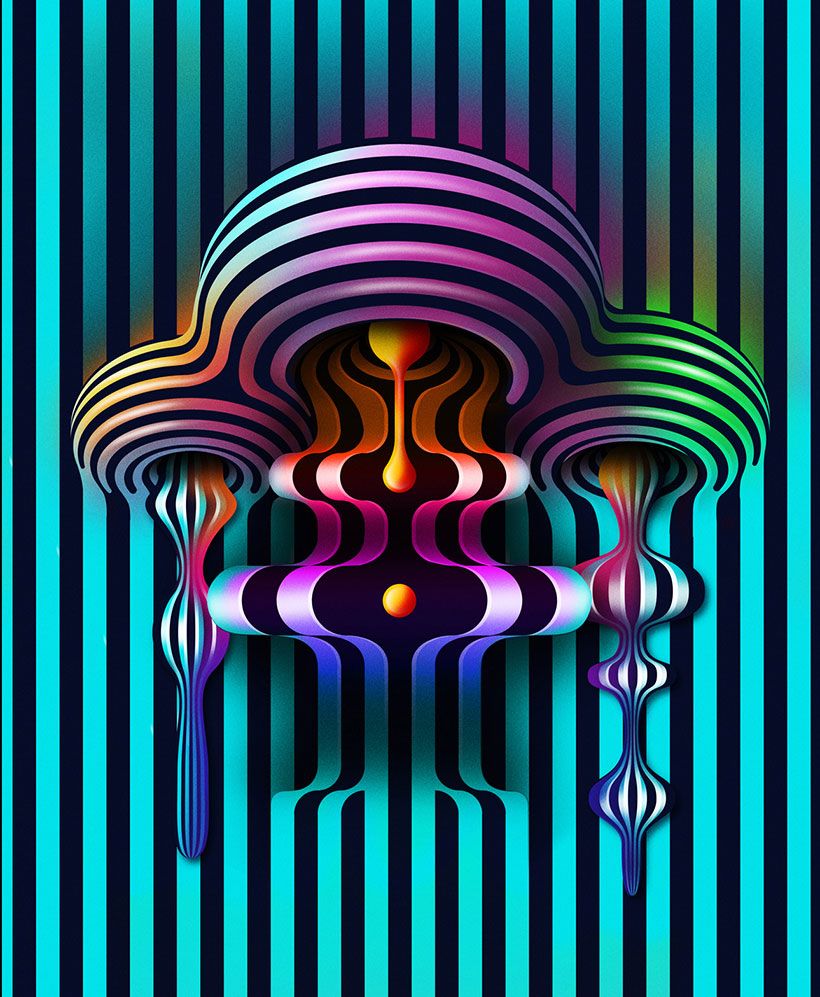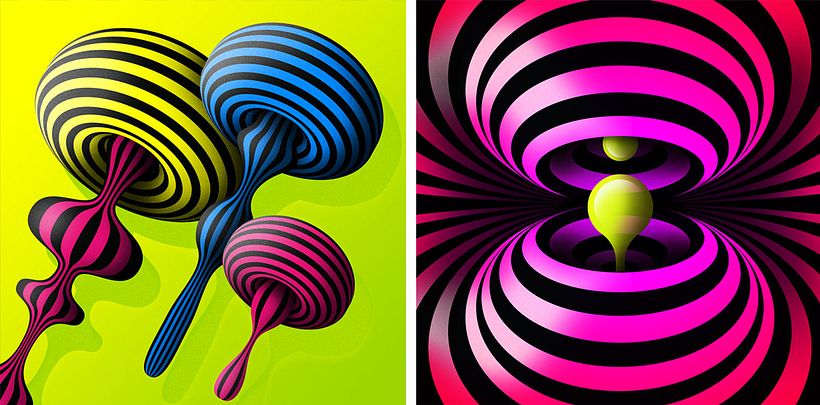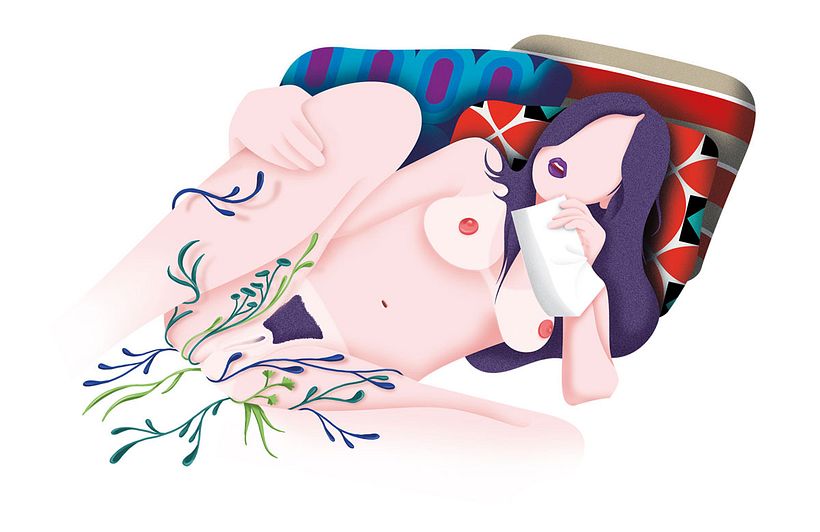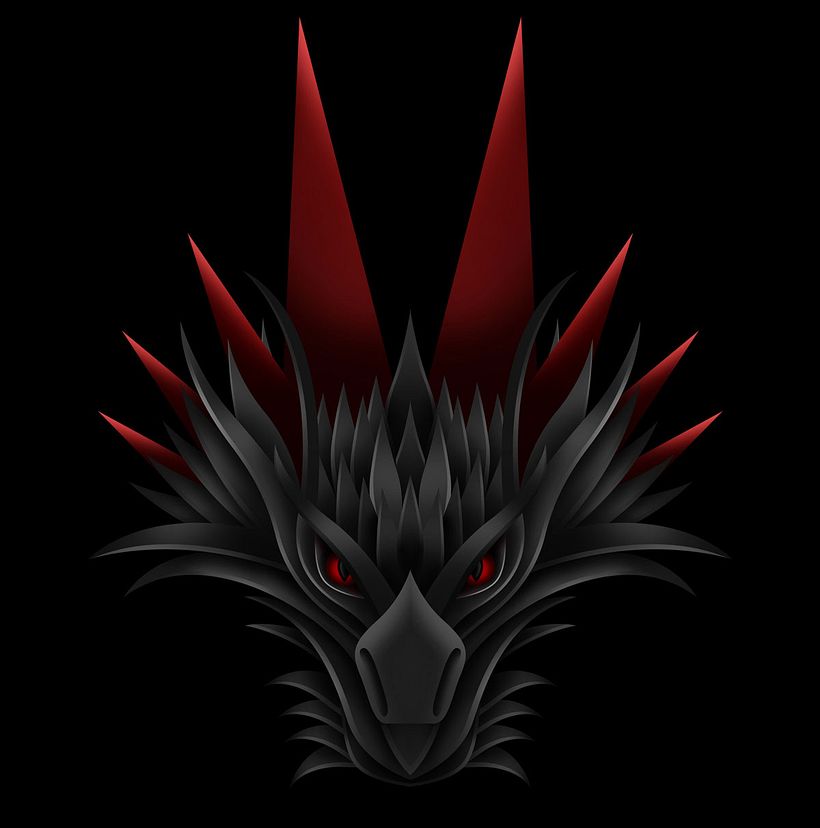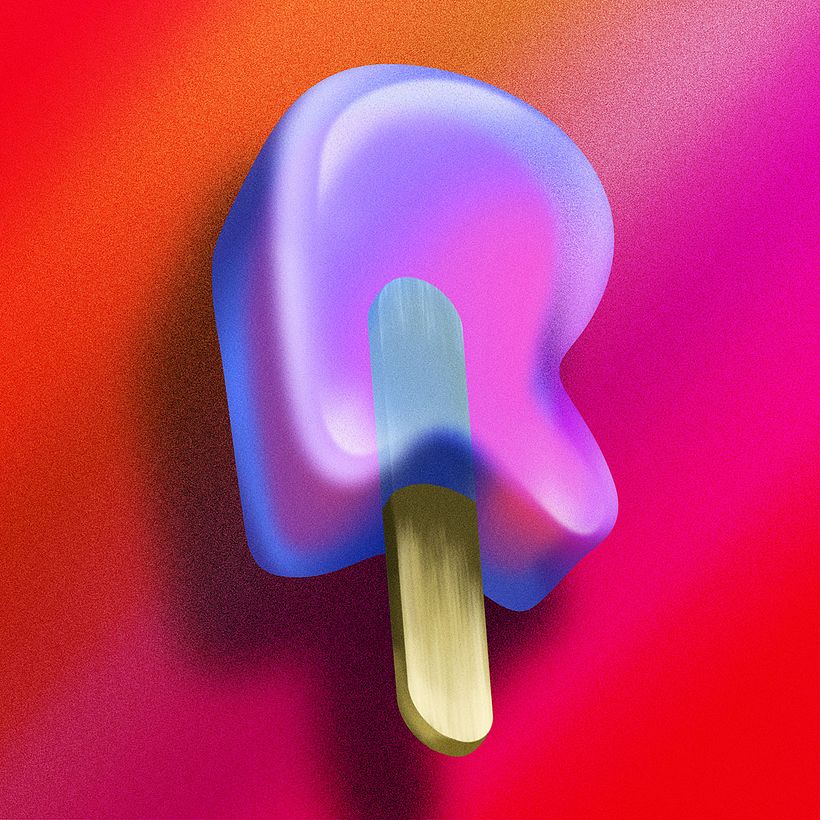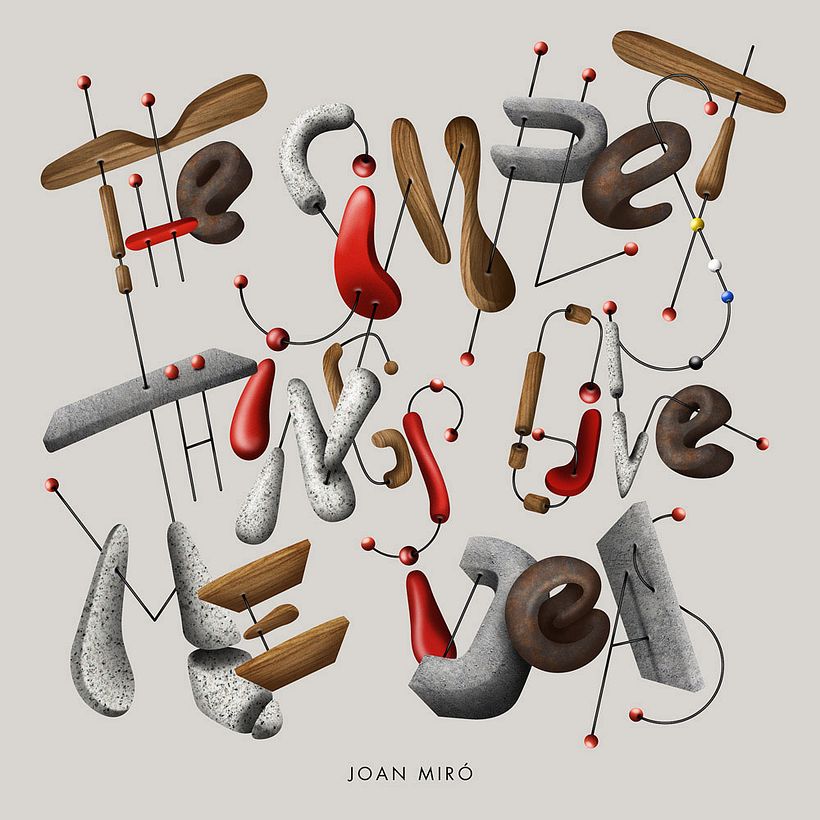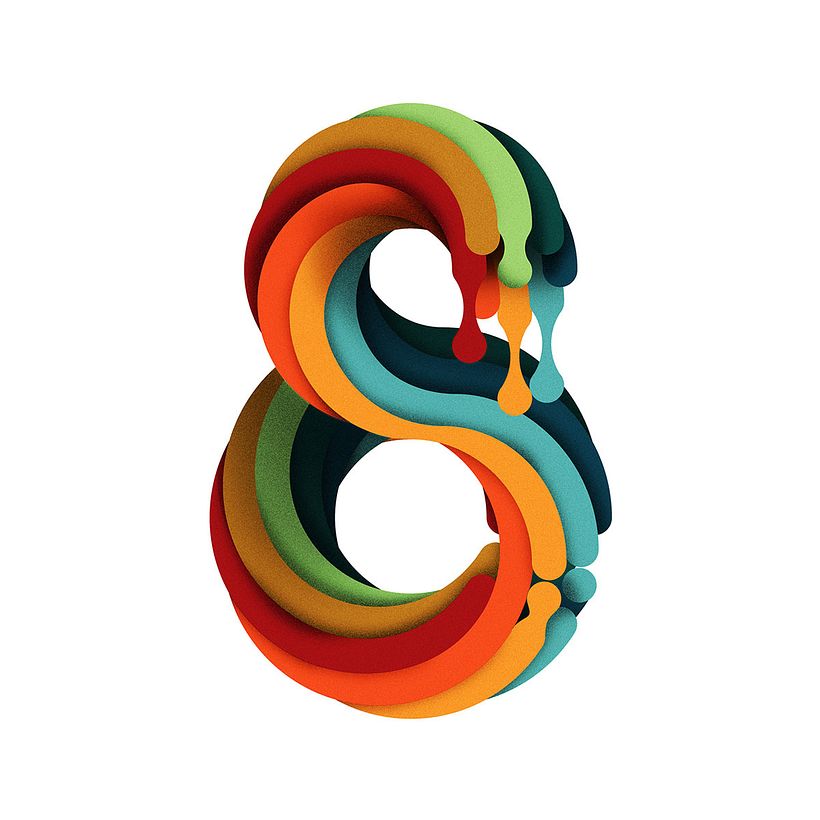
DAQ: sexo, tipografía y psicodelia
Llevaba años trabajando para agencias y estudios de diseño, pero decidió establecerse como ilustrador por su cuenta.
Esto ha permitido a DAQ, un diseñado, ilustrador y creador de lettering de Barcelona, dedicarse a tiempo completo a trabajar para sus propios clientes y a desarrollar proyectos personales con total libertad. El dinamismo es una de sus señas de identidad, y es que casi la totalidad de sus diseños gozan de unas líneas que, combinadas con el total control de las luces y sombras que hace Daq, consiguen transformar una ilustración plana en un trabajo casi en tres dimensiones.
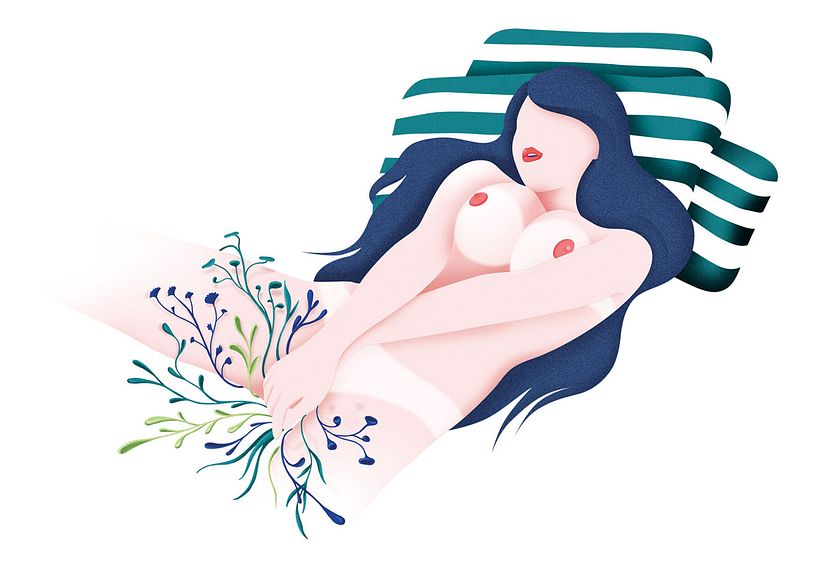
Uno de sus últimos trabajos es la serie de ilustraciones que realizó para la edición francesa de Stylist Magazine sobre la masturbación femenina, en los que muestra el orgasmo de la mujer de forma natural y sin tapujos.
Pero la mayoría de su obra gira en torno a las letras y los diseños hipnóticos y psicotrópicos llenos de curvas y movimiento.
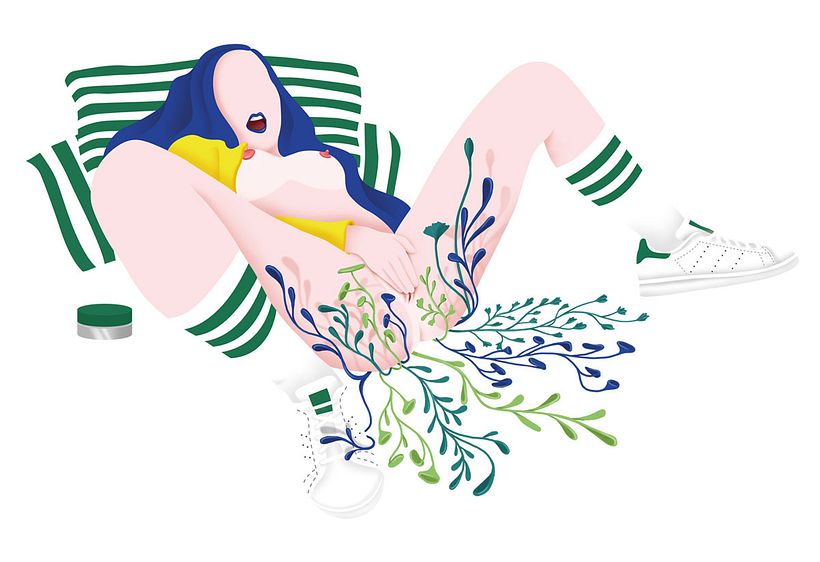
DAQ es un artista integral, lo que quiere decir que se ocupa del desarrollo creativo desde el inicio hasta el final. Controlando proceso desde el boceto del concepto hasta el último detalle de la realización del diseño, se empeña en crear trabajos diferentes e imaginativos y esa dedicación es evidente a la hora de contemplar los resultados.
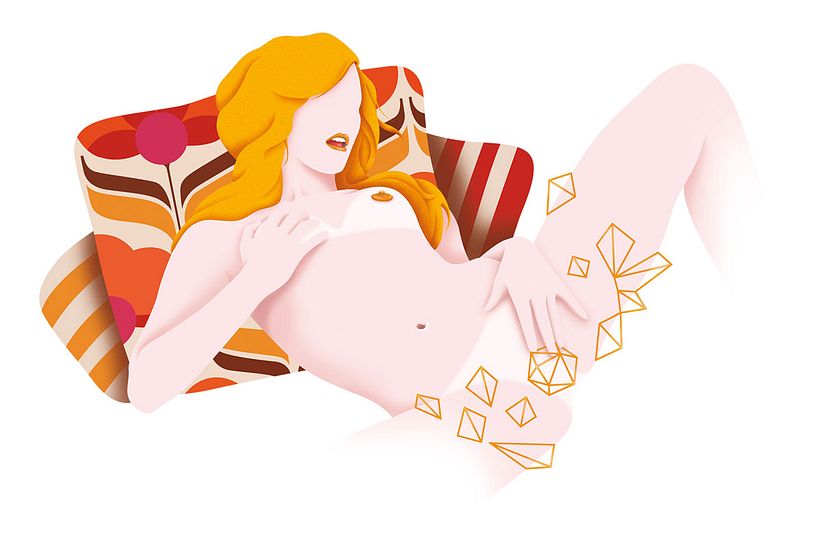
DAQ ha trabajado para grandes agencias como Lola, Y&R, McCann o DDB y empresas importantes como Adobe, Wacom, Notegraphy, Telefónica, Unicef, Penguin Books, etc.